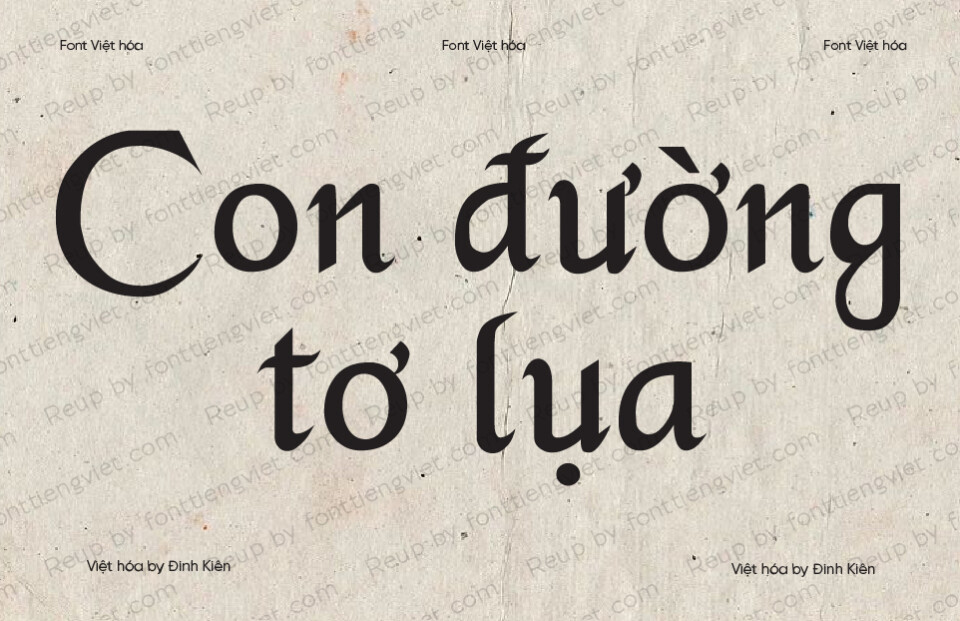
Trong thời đại kỹ thuật số, việc trình bày tài liệu học tập, báo cáo hay thậm chí là bài thi tốt nghiệp không chỉ yêu cầu nội dung chất lượng mà còn cần yếu tố thẩm mỹ cao. Việc lựa chọn một kiểu Font Chữ phù hợp có thể tạo nên sự khác biệt lớn. Đối với cộng đồng học sinh, sinh viên, và các nhà giáo dục tại Việt Nam, nhu cầu về những bộ font đẹp, chuyên nghiệp và quan trọng nhất là phải được Việt hóa hoàn chỉnh luôn rất cao. Trong số đó, Font Việt hóa UTM Chancery nổi lên như một lựa chọn hàng đầu, kết hợp hoàn hảo giữa nét cổ điển, thanh lịch và khả năng hiển thị tiếng Việt mượt mà. Bài viết này sẽ đi sâu vào những đặc điểm khiến Font Việt hóa UTM Chancery trở thành công cụ không thể thiếu trong kho tài liệu của bạn.
Font Việt hóa UTM Chancery: Đặc Điểm Nổi Bật và Lý Do Được Ưa Chuộng
Font Việt hóa UTM Chancery thuộc dòng chữ viết tay (script font) nhưng được thiết kế với độ rõ ràng cao, lấy cảm hứng từ phong cách Chancery cổ điển. Đây là một bộ font do nhóm UTM (Unique Typeface Makers) phát triển và tối ưu hóa đặc biệt cho người dùng Việt Nam. Khác biệt lớn nhất so với các phiên bản quốc tế là sự bổ sung đầy đủ các ký tự dấu, ký tự đặc biệt của tiếng Việt, giúp người dùng gõ văn bản mà không gặp lỗi hiển thị (lỗi ô vuông hay mất dấu). Phong cách Chancery mang lại cảm giác trang trọng, lịch thiệp, rất phù hợp khi sử dụng trong các thiệp mời, bằng khen hoặc tiêu đề của các bài nghiên cứu khoa học. Sự trau chuốt trong từng nét chữ giúp tài liệu của bạn trở nên chuyên nghiệp hơn rất nhiều. Việc font được Việt hóa chuẩn chỉnh là yếu tố then chốt giúp học sinh cấp 3 và sinh viên dễ dàng hoàn thành các bài tập lớn yêu cầu tính thẩm mỹ cao.
Nguồn gốc và Phong cách của UTM Chancery
Phong cách Chancery đã tồn tại từ nhiều thế kỷ, nổi tiếng với các đường nét bay bổng nhưng vẫn giữ được tính dễ đọc. Khi được Việt hóa bởi UTM, bộ font này không chỉ kế thừa vẻ đẹp đó mà còn được tinh chỉnh để các dấu mũ, dấu huyền, sắc, hỏi, ngã, nặng hòa hợp tuyệt đối với tổng thể phông chữ. Điều này loại bỏ hoàn toàn rào cản kỹ thuật thường gặp khi sử dụng font nước ngoài cho tiếng Việt. Đây là lý do khiến nhiều trường học và cơ sở giáo dục tin tưởng lựa chọn font chữ này cho các tài liệu chính thức, từ các thông báo quan trọng đến các chứng chỉ cho sinh viên.
Ứng Dụng Thực Tế UTM Chancery Trong Học Tập và Thi Cử
Không chỉ dừng lại ở tính thẩm mỹ, Font Việt hóa UTM Chancery còn có ứng dụng rộng rãi trong môi trường giáo dục. Đối với học sinh chuẩn bị cho kỳ thi tốt nghiệp, việc thiết kế một cuốn kỷ yếu đẹp hoặc trình bày một bài báo cáo khoa học có thể sử dụng UTM Chancery để tạo điểm nhấn ở phần tiêu đề hoặc trích dẫn quan trọng. Nó giúp bài viết của bạn nổi bật hơn so với các văn bản sử dụng các font chữ quá phổ thông như Times New Roman hay Arial, thể hiện sự đầu tư nghiêm túc vào sản phẩm học tập.
Các ứng dụng phổ biến bao gồm:
- Thiết kế Bài giảng: Giáo viên sử dụng để tạo tiêu đề slide thuyết trình ấn tượng.
- Bìa Tiểu luận và Luận văn: Mang lại vẻ trang trọng, học thuật cho tài liệu, đặc biệt là các báo cáo yêu cầu sự cổ điển.
- Thiệp mời tốt nghiệp: Phong cách lịch thiệp, phù hợp với sự kiện quan trọng.
- Đồ án môn học: Giúp các bản vẽ kỹ thuật hoặc sơ đồ có chú thích rõ ràng, đẹp mắt, dễ dàng được đánh giá cao bởi giảng viên.
Nhiều chuyên gia thiết kế tài liệu học tập cho rằng các nội dung được trình bày bằng font chữ dễ đọc, có tính thẩm mỹ cao thường giữ chân người xem lâu hơn, điều này gián tiếp cải thiện trải nghiệm người dùng trên các nền tảng số hóa tài liệu học tập và giúp học sinh tiếp thu kiến thức hiệu quả hơn.
Tóm lại, Font Việt hóa UTM Chancery là một tài nguyên quý giá, đặc biệt đối với học sinh, sinh viên và giáo viên đang tìm kiếm sự cân bằng giữa tính chuyên nghiệp, thẩm mỹ và khả năng hỗ trợ tiếng Việt hoàn hảo. Với phong cách thanh lịch, dễ đọc và quá trình cài đặt đơn giản, nó xứng đáng là lựa chọn hàng đầu cho các dự án từ tiểu luận nhỏ đến báo cáo tốt nghiệp quan trọng. Đừng ngần ngại bổ sung bộ Font Chữ đặc biệt này vào bộ sưu tập của bạn để nâng cao chất lượng trình bày tài liệu. Hy vọng những thông tin chi tiết về Font Việt hóa UTM Chancery đã giúp bạn có cái nhìn rõ ràng hơn về công cụ tuyệt vời này và ứng dụng nó thành công trong học tập.